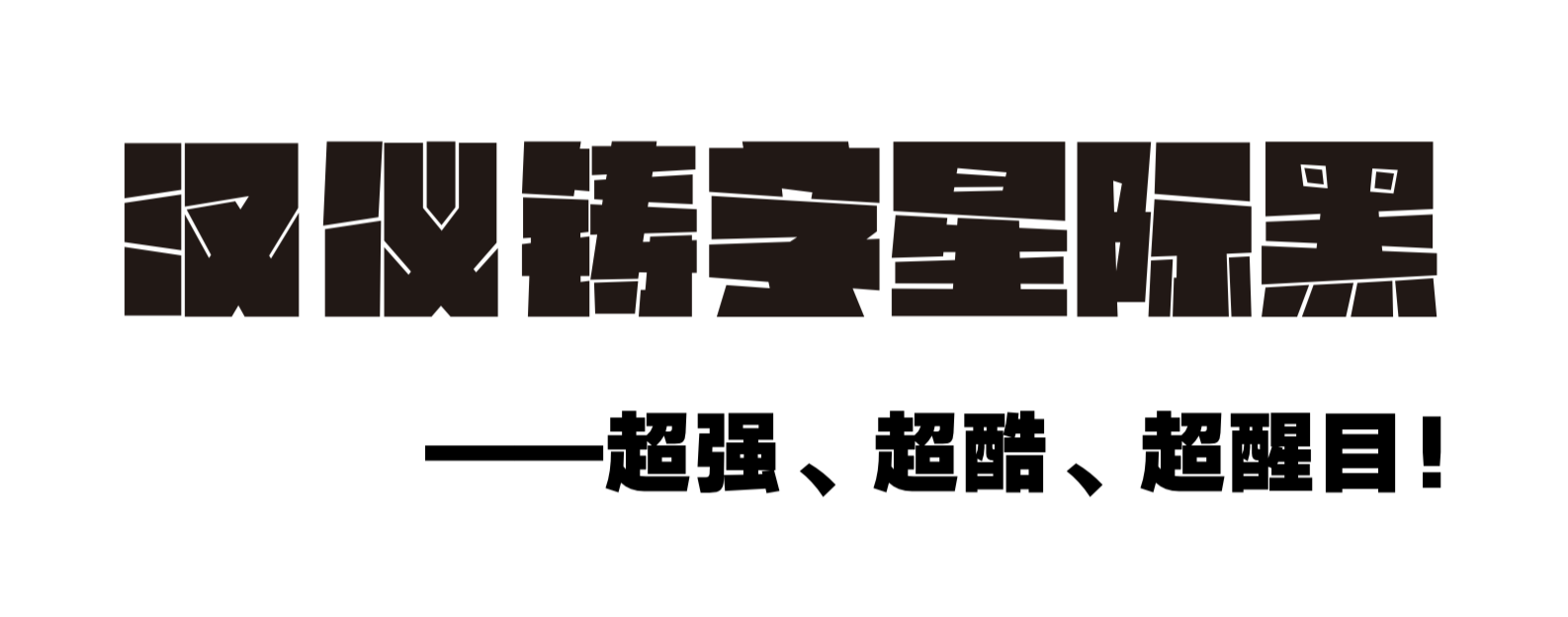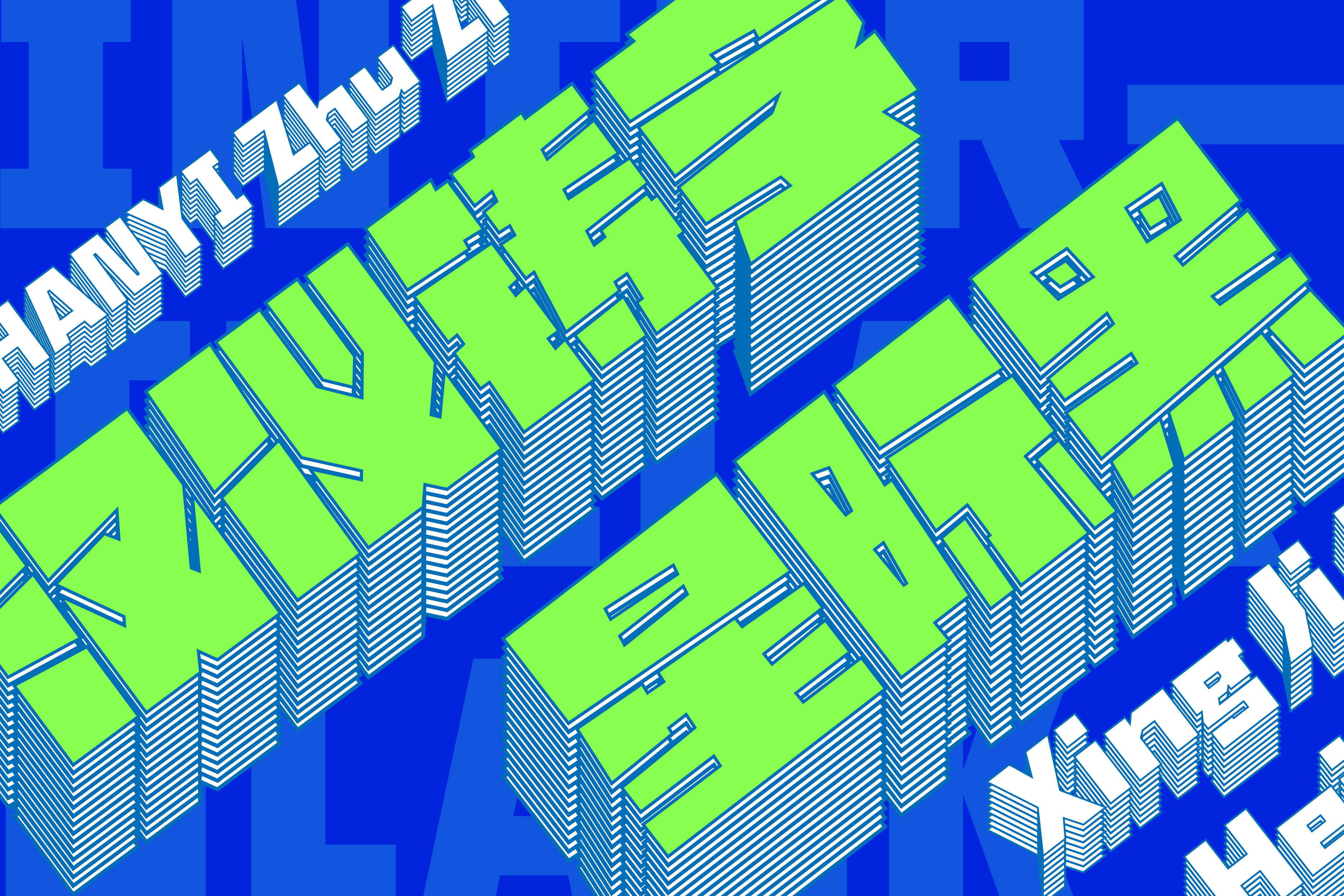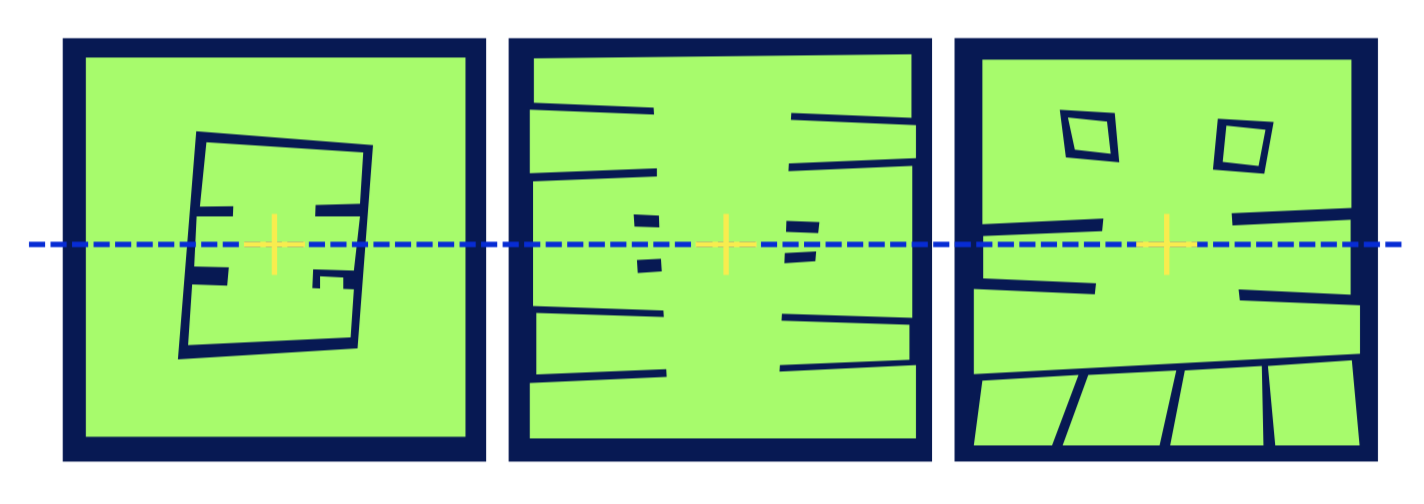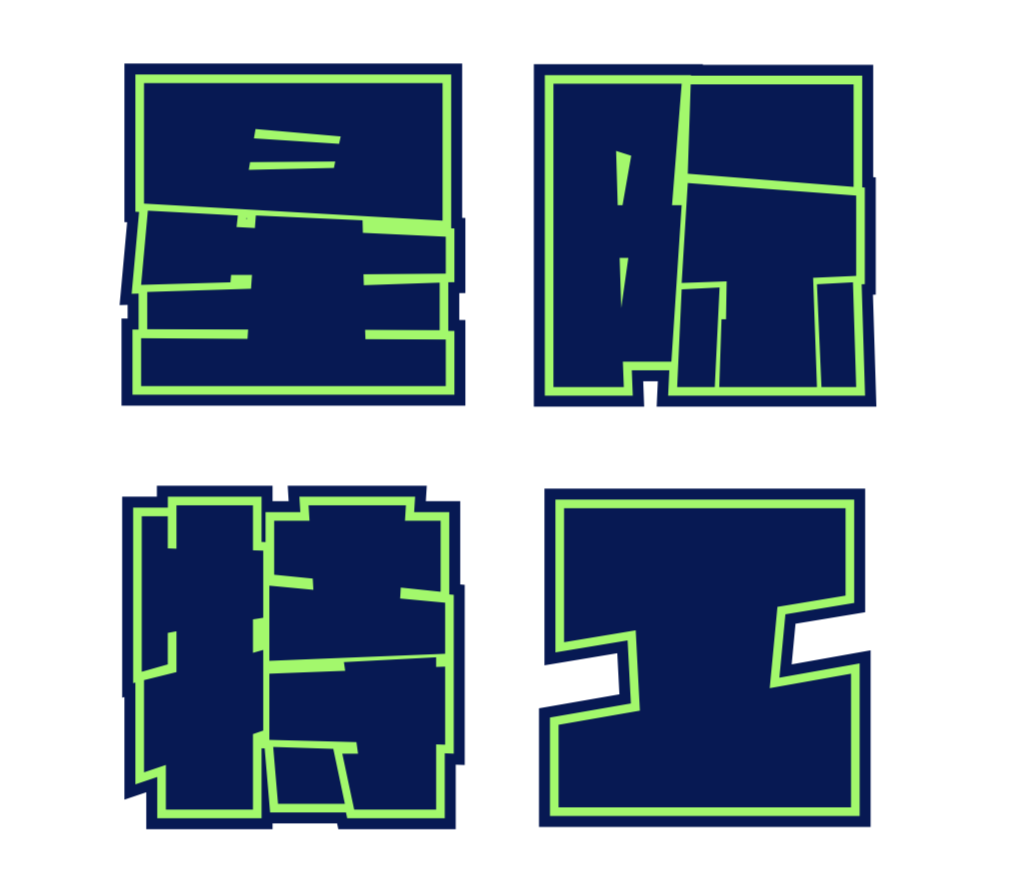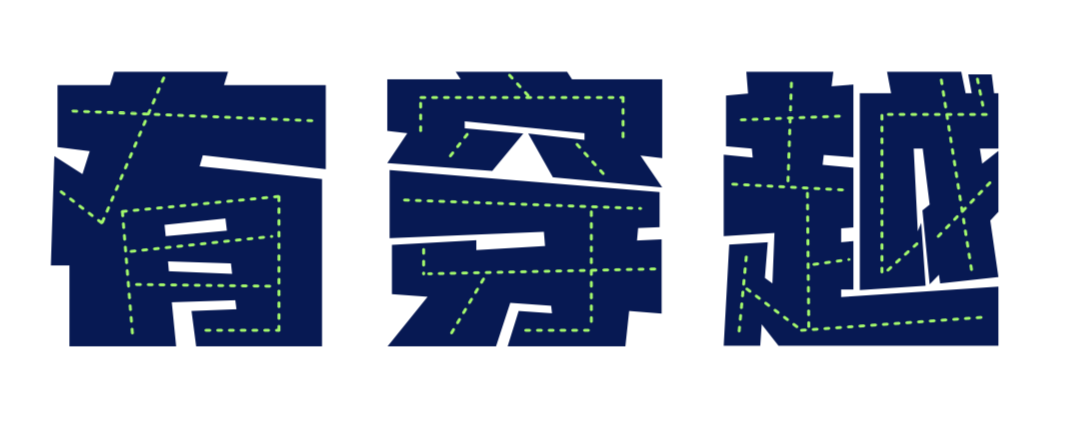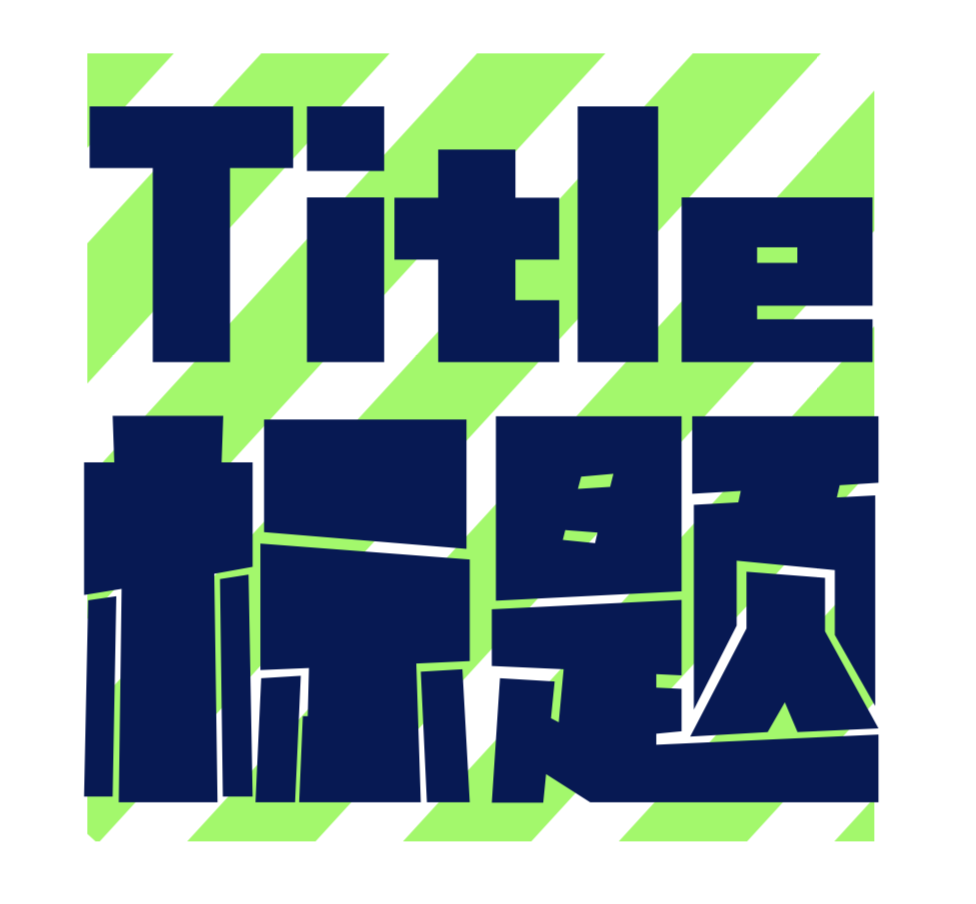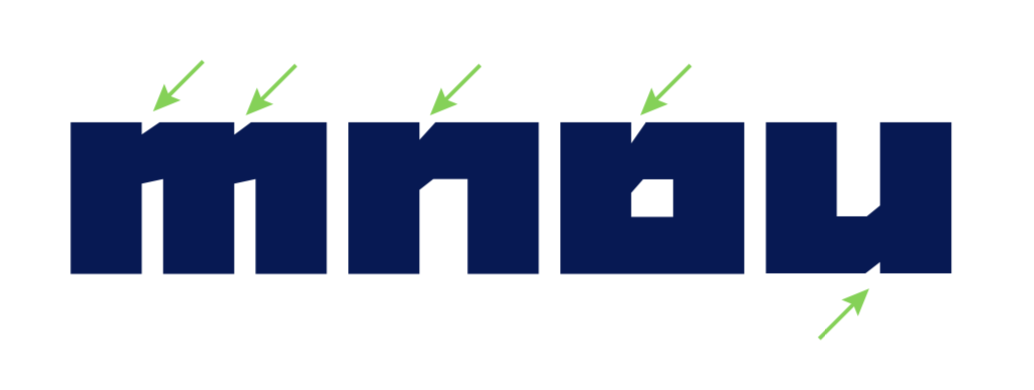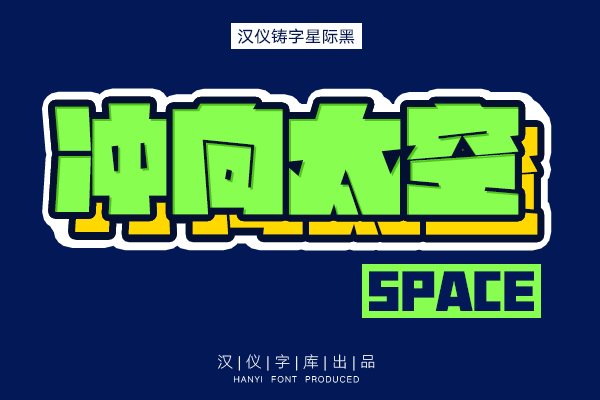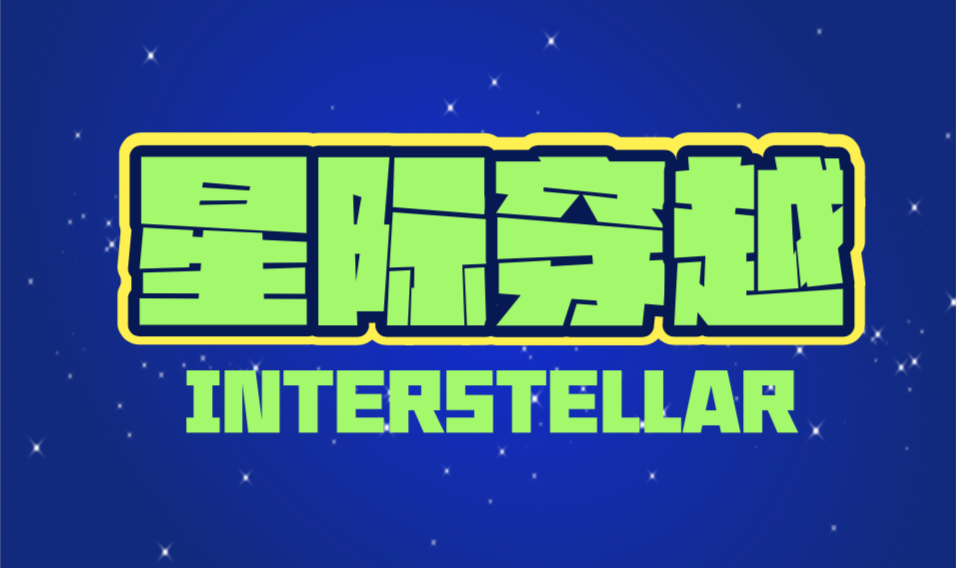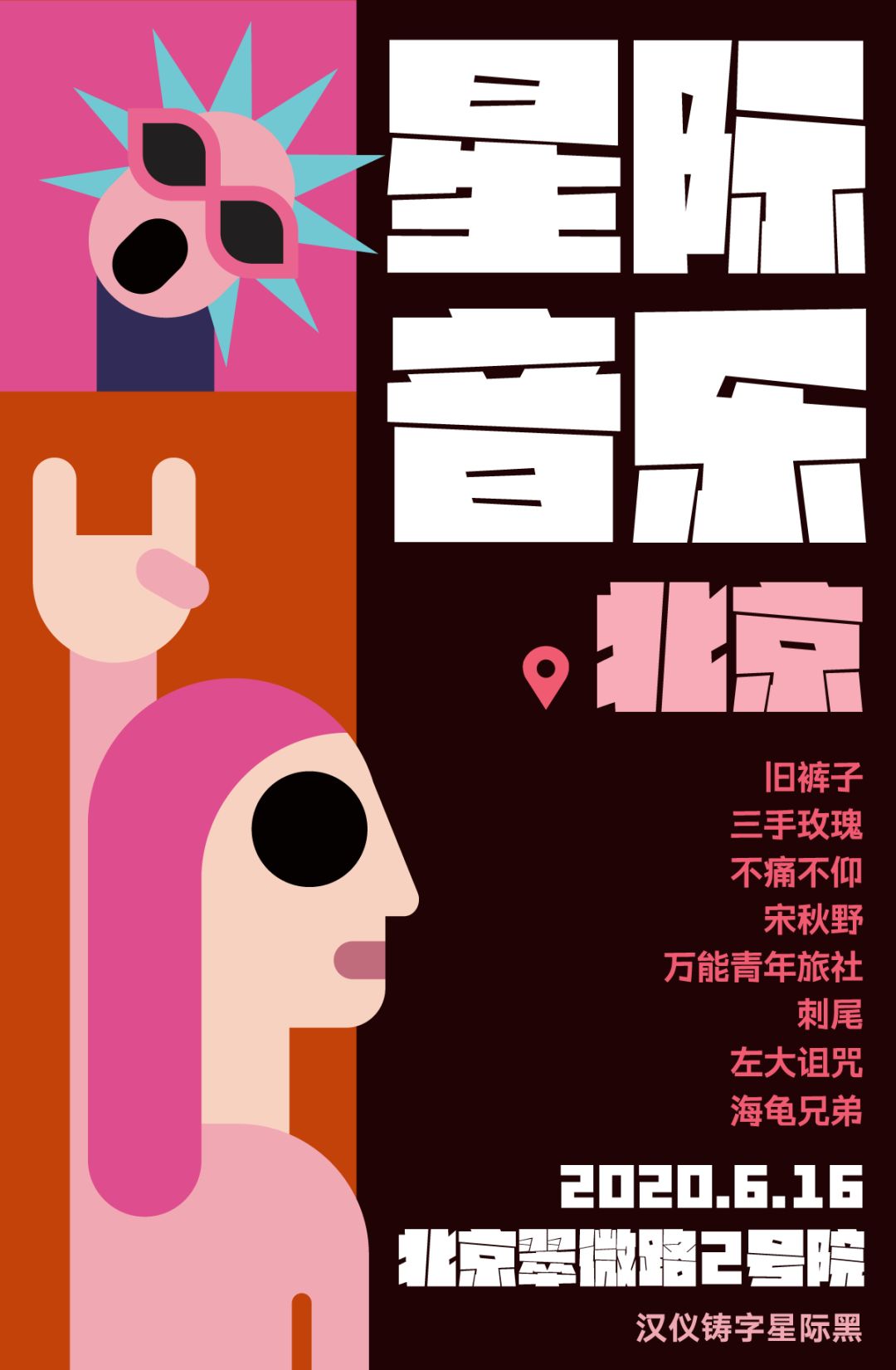
汉仪铸字星际黑字体介绍,汉仪铸字星际黑设计思路
汉仪铸字星际黑 | 整体特点
“汉仪铸字星际黑”是汉仪旗下的“铸字社工作室”打造的一款美术标题字。它的字型方正,笔画粗重,字面饱满,整体透露着一种稳重的力量,笔画的高低错落使字体多了一些生动活泼的感觉。适用于少量字数的标题排版设计。
汉仪铸字星际黑 | 字形特点
“汉仪铸字星际黑”的字符长宽比为1:1,字符重心稳定,字体空间结构紧凑,呈现出强势醒目的字体性格。在标题字的排版使用中,可使版面达到整齐干净而又吸引人眼球的视觉效果。
汉仪铸字星际黑 | 笔画特点
“汉仪铸字星际黑”打破了传统字体的笔形和结构,将笔画凝练为简练的几何图形,使字形更趋向于图形化处理。
“汉仪铸字星际黑”严谨中透着活泼,笔画间的组合变化自由生动、精准巧妙。横笔的形状为梯形,头尾粗细不一,让字体笔画之间的空间呈现出高低不同的变化。
“汉仪铸字星际黑”的所有笔画均为直线相切。通过对笔画粗细及黑白空间的相对调整,使字体无论有多少笔画都能保持均匀统一的灰度,既保留了字体特征又保证了文字的可识别性。
汉仪铸字星际黑 | 中西文匹配
“汉仪铸字星际黑”西文字母保留了中文字体的特点,使西文也同样传达出统一、方正的秩序感,搭配标题字使用时,会有更好的呈现效果。
“汉仪铸字星际黑”的西文小写字母在笔画相接处,做了灵活的缺角处理。为笔画粗壮的黑体增添了一些呼吸感和趣味性。
汉仪铸字星际黑 | 排版效果
在将“汉仪铸字星际黑”作为大标题用字体时,字号在40pt以上使用,字形会有更清晰的表达,在版面的排版使用中会达到醒目和冲击力强的视觉效果。
汉仪铸字星际黑 | 应用展示